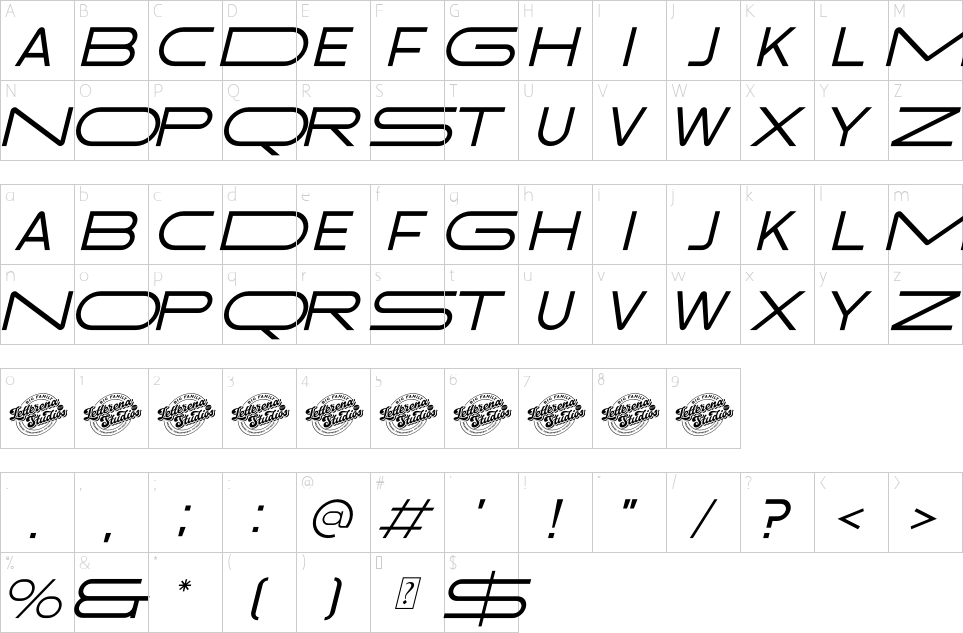
A Mugesta Font é uma opção elegante e versátil para designers e criadores de conteúdo no Brasil. Desenvolvida pela Storytype Studio, esta fonte ganhou mais de 1.530 downloads, demonstrando seu valor e popularidade no mercado de fontes gratuitas. Com um design arredondado e agradável aos olhos, a Mugesta é perfeita para se adequar a um grande range de projetos, desde materiais gráficos para blogs e revistas até aplicações digitais e design de interfaces de usuário. A fonte é uma excelente escolha para quem busca um look moderno e sofisticado sem ter que investir em licenças de fontes premium. Se você está buscando uma fonte de qualidade para o seu próximo projeto, a Mugesta é uma excelente opção que não compromete em termos de estilo ou funcionalidade.